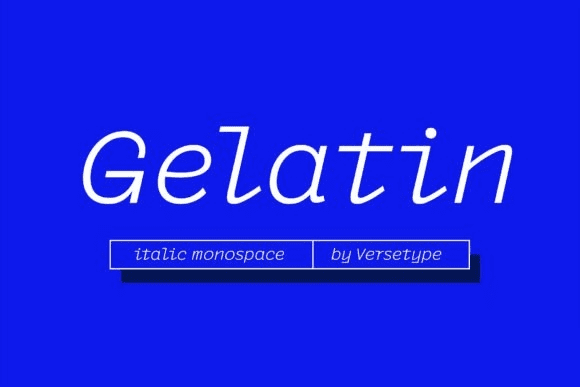
Название: Gelatin Font (2021)
Gelatin - это адаптируемый и чистый шрифт sans serif.
Его можно легко подобрать к невероятно большому набору проектов, поэтому добавьте его в свои творческие идеи и обратите внимание, как он их выделяет!